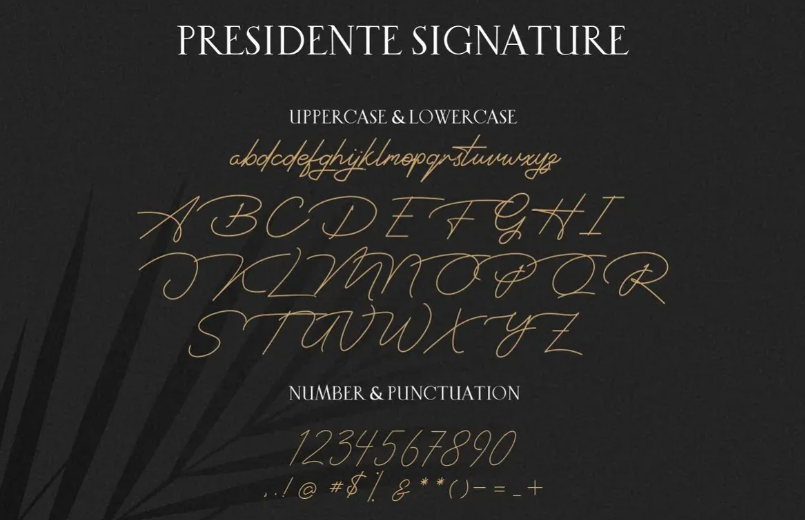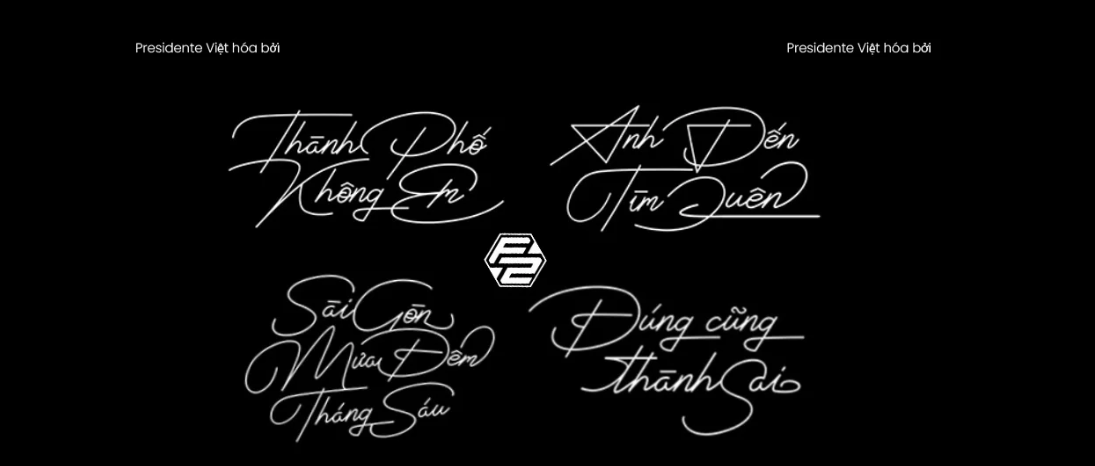
Font Presidente Việt hóa là bộ phông chữ có chân (Serif) mang phong cách cổ điển, sang trọng và đậm chất di sản, lấy cảm hứng từ những bảng hiệu thuộc địa và nhãn hiệu rượu vang thượng hạng thế kỷ trước. Với sự kết hợp tinh tế giữa cấu trúc chữ đĩnh đạc, các đường chân chữ sắc sảo và độ tương phản nét thanh đậm tinh tế, phông chữ này là lựa chọn đỉnh cao cho các thiết kế nhãn dán rượu mạnh, bao bì cà phê hạt hảo hạng, hộp quà tặng doanh nhân và bộ nhận diện thương hiệu mang hơi hướng Vintage Luxury. Doozypack.vn cung cấp link Font Presidente Việt hóa Download chuẩn kỹ thuật, giúp bạn sở hữu phông chữ đẳng cấp này, hỗ trợ đầy đủ tiếng Việt để tự tin thiết kế bao bì và bộ nhận diện thương hiệu chuyên nghiệp.
Đặc điểm thẩm mỹ độc đáo của bộ font Presidente
Presidente không đi theo sự tối giản hiện đại của các phông chữ hình học; nó mang đến một ngôn ngữ thị giác đầy tính quyền lực, tái hiện trọn vẹn sự uy nghi và đẳng cấp của các thương hiệu lâu đời.
Phong cách Vintage Serif mang hơi thở hoàng gia và cổ điển
Đặc trưng lớn nhất của Font Presidente Việt hóa là cấu trúc chữ mang tính di sản cao với các đường nét dứt khoát, uy nghiêm. Thân chữ thẳng đứng kiêu hãnh kết hợp cùng các góc chân chữ sắc lẹm tạo nên một khối văn bản vô cùng vững chãi, uy tín. Khi đặt Presidente làm tiêu đề trên bao bì, thương hiệu của bạn sẽ ngay lập tức toát lên vẻ ngoài đắt tiền, trường tồn và mang chiều sâu lịch sử.
Độ tương phản nét thanh đậm sắc sảo tạo điểm nhấn uy quyền
Các ký tự của Font Presidente Việt hóa Free sở hữu tỷ lệ tương phản rõ rệt giữa các nét dọc dày dặn và nét ngang thanh mảnh. Tỷ lệ này giúp tiêu đề bản thiết kế giữ được sự thanh thoát, quý phái mà không hề gây cảm giác nặng nề, rất phù hợp với các mẫu hộp giấy định vị ở phân khúc thượng lưu.
Ưu điểm nổi bật của bản Font Presidente Việt hóa
Khi ứng dụng các phông chữ cổ điển vào thị trường trong nước, sự chỉn chu về dấu câu là yếu tố quyết định đến tính chuyên nghiệp của ấn phẩm:
- Khắc phục triệt để lỗi dấu tiếng Việt: Phiên bản Việt hóa đã được đội ngũ thiết kế trau chuốt thủ công từng dấu câu. Các dấu sắc, huyền, hỏi, ngã, nặng được vẽ với tỷ lệ cân đối, đặt ở vị trí thoáng đãng so với thân chữ, không gây cảm giác chắp vá hay đè nét làm mất tính thẩm mỹ cổ điển.